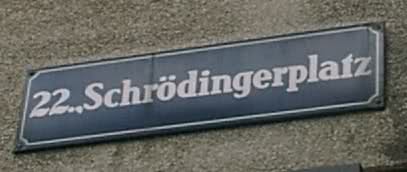
Schrift von österreichischem Straßenschild gesucht
Weiß wer welche Font das auf dem Schild ist?
Ist von einem Wiener Straßenschild.
Soll das nachbauen, allerdings mit einem anderen Text.
Jene gestaltete er:
Aigrette (1939)
Bernhard Antiqua (1912)
Bernhard Bold Condensed
Bernhard Brushscript SG
Bernhard Fashion (1929)
Bernhard Fraktur
Bernhard Gothic (1930)
Bernhard Handschrift (1928)
Bernhard Modern (1937)
Bernhard Privat (1919)
Bernhard Schönschrift
Bernhard Tango
Concerto Rounded SG
Lilli
Lucian (1932), später wiederaufgelegt als Belucian
Negro (1930), später wiederaufgelegt als Berlin Sans
Jene gestaltete er …
Ausschließlich jene? Das t sieht sehr nach der Bernhard bold condensed aus, es müßte doch eigentlich auch eine normallaufende bold geben. Es baut doch niemand eine ausschließlich eine Condensed-Version, oder?
Ich werd wohl die Bernhard Bold Condensed nehmen und sie breit stellen. Witzigerweise gibt es anscheinend keinen "normalen" Bold Schnitt.
Aber das Resultat ist beim Breitstellen auch annehmbar.
hoffentlich kommt kein "g" vor - das ist nämlich schon ganz, ganz anders ...
(aber was besseres weiß ich leider auch nicht.)
Spät, aber hier die Antwort:
Wiener Norm heißt die Schrift.